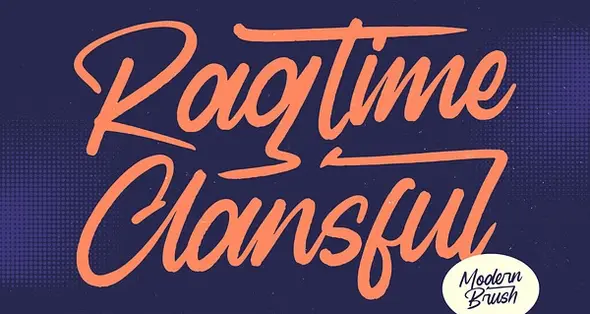
• Ragtime Clansful Modern Brush Font
فونت انگلیسی دست نویس پیوسته
Ragtime Clansful که توسط Letterena ارائه شده، یک فونت اسکریپت لوکس و مدرن است. این فونت برای انواع پروژه‌ها مانند: لوگوها، پروژه‌های برندسازی، طراحی لوازم خانگی، بسته‌بندی محصول، ماگ، نقل‌قول‌ها، پوسترها، کیسه‌های خرید، تی‌شرت‌ها، جلد کتاب، کارت‌های ویزیت، کارت‌های دعوت، کارت‌های تبریک، برچسب‌ها، عکاسی، واترمارک، رویدادهای خاص و تمامی پروژه‌های لوکس و زیبای دیگری که به حس‌وحال اسکریپت‌های لوکس نیاز دارند، مناسب است.
ویژگی‌ها:
• 185 لیگاچور، 40 حرف جایگزین و 6 سوَش (Swash)
• حروف بزرگ و کوچک
• اعداد
• علائم نگارشی (استاندارد OpenType)
• اکسنت‌ها (کاراکترهای چندزبانه)
• لیگاچورها و مجموعه استایل‌های جایگزین
Ragtime Clansful - Modern Brush Font , from Letterena, is a Luxury Script font, suitable for any projects such as: logos, branding projects, homeware designs, product packaging, mugs, quotes, posters, shopping bags, t-shirts, book covers, name card, invitation cards, greeting cards, label, photography, watermark, special events, and all your other luxury and beautiful projects that need a Luxury Script taste.
Features :
- 185 Ligature 40 Alternate & 06 Swashes
- Uppercase and Lowercase
- Numerals
- Punctuations (OpenType Standard)
- Accents (Multilingual Characters)
- Ligatures and Alternative Style Stylistic Set